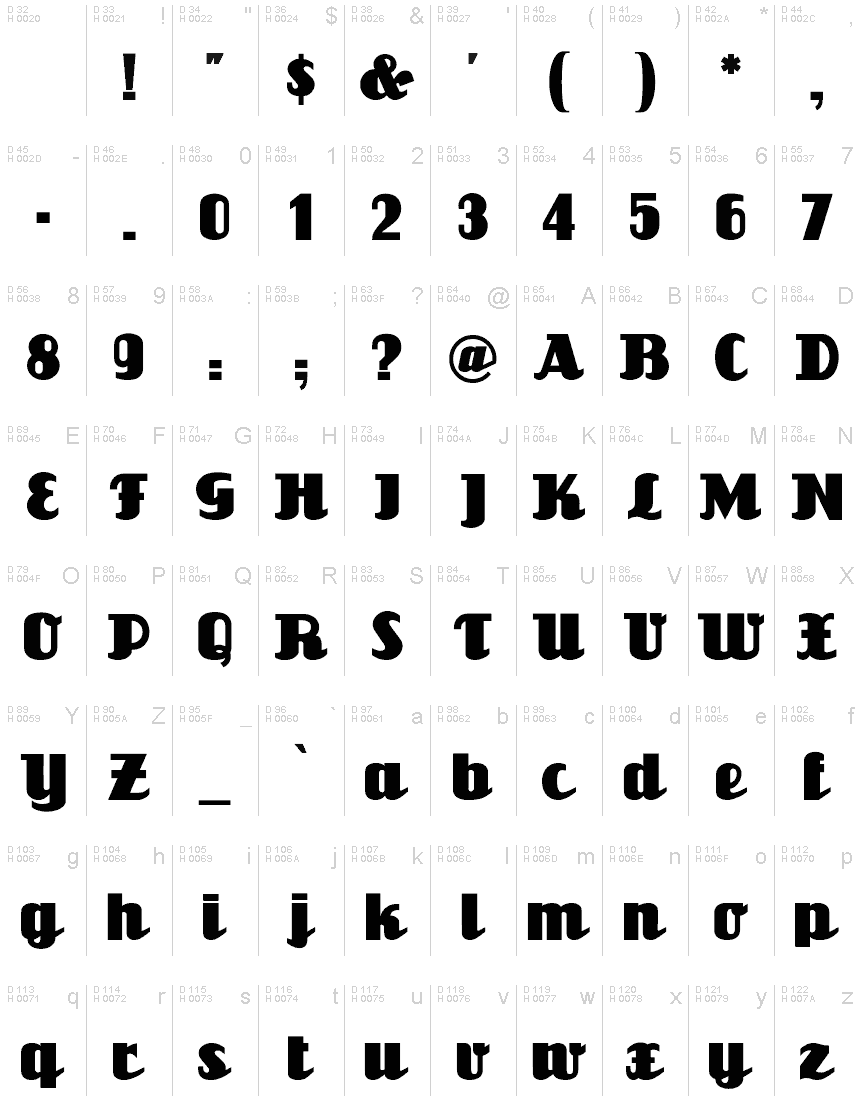
Unicorn NF 字体
Unicorn NF
沉浸在由 Nick Curtis 设计的 Unicorn NF 的怀旧氛围中,这是一款极具特色的字体。作为 Unicorn 系列的一员,这款超粗、略微加宽的显示字体散发着复古魅力,捕捉到了往昔时代的精髓。Unicorn NF 浓重的笔触和灵动的曲线,为任何视觉设计都增添了一抹奇思妙想和鲜明的个性。
凭借其扎实的字形和略微拉伸的外观,Unicorn NF 不仅仅是页面上的文字,更是一个引人注目的视觉焦点。其美学风格让人联想到复古广告和标识,非常适合那些旨在唤起怀旧感,或在经典精致中融入现代风尚的项目。
无论是装饰书籍封面、作为活动海报的标题,还是为品牌物料增添个性,Unicorn NF 的时尚魅力都足以适应各种创意需求。拥抱这款复古风格字体的独特魅力,让您的设计留下难忘的印象。